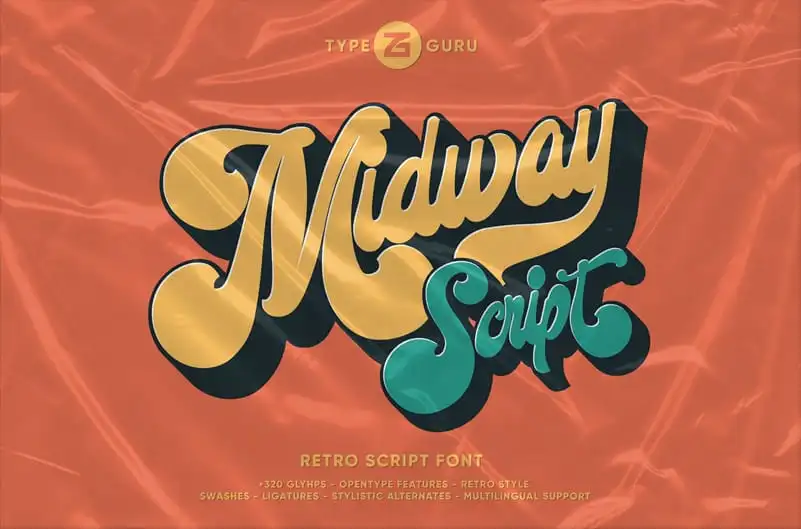
Midway Display Font – Fonte Grátis
Midway Display Font
A Midway Display Font é uma paixanteira coleção de tipo que surge dos talentos inovadores de Ardana Putra. Esta fonte destacada tem um toque vintage, oferecendo aos designers e criativos a oportunidade de criar designs impactantes. Perfeita para aplicação em logotipos, headlines, sinalizações e diversos outros formatos formais como convites, rótulos, logos, revistas, livros, cartões de cumprimentos nupciais, embalagens, moda, maquiagem, materiais de escritório, romances, selos ou qualquer tipo de fim de publicidade. Com sua forte tipografia vintage e um toque sofisticado que remete aos tempos antigos da design gráfico, a Midway Display Font é o tipo perfeito para criar designs de alta qualidade. Seja você um designer de logotipos, criador de materiais de embalagem ou editor de revistas, essa fonte vai tornar sua criação mais imponente e memorável.